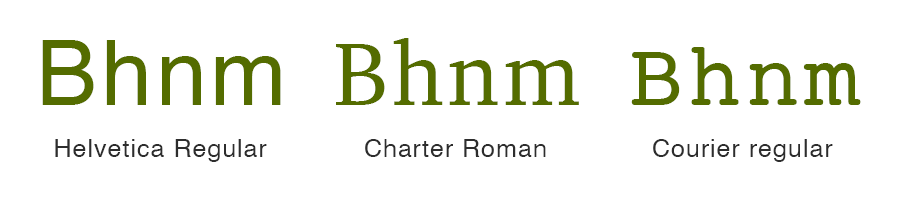
罗马字母的基本形状非常的一致。尽管它们可能经过各种装饰,如添加衬线、花体字样,但其基本结构保持不变。例如,字母B主要由一个直立的笔画和两个半圆形部分(碗状)构成。至于字母m,它基本可以看作是字母n多了一个额外的驼峰;而n则类似于一个上升部分被截断的h的形状。
但是,小写字母a和g存在两种截然不同的书写形式。一种是较为简约的“1层型”式a(也被称作单层a),另一种是较为复杂的“2层型”式a。同样地,小写字母g也有单层与双层之分,其中双层g有时被形象的称为“碗形”和“环形”或“眼镜式g”。
单层型的字母更现代化,是普遍的书写形式。两层的 a 和 g 在罗马字或直立字体样式中更为常见。这两个版本均源自2世纪时的大写字母形式及随后在手抄本中演变出的“安色尔体(Uncial letters)”。